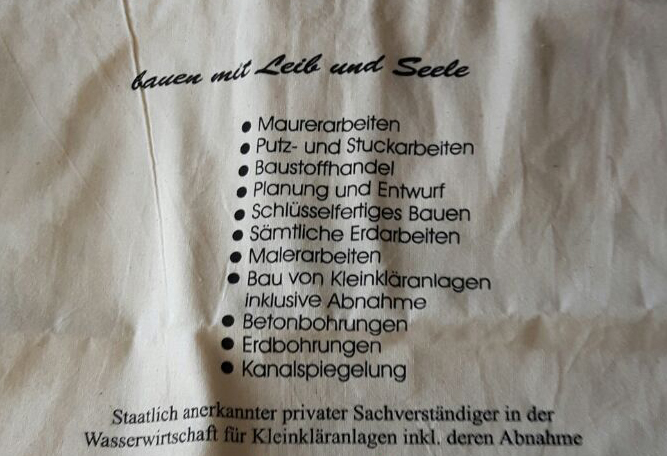
geometrische serifenlosen Linearantiqua gesucht
ich suche für einen Bekannten, die auf dem Bild zu sehenden Schriftarten.
Bei der Handwritten handelt es sich um die Brush script Std.. Hab ich grade noch rausgefunden. :-)
Könnt Ihr mir mit der Grotesk und der Serifenschrift helfen?
Leider handelt es sich um eine Stofftasche. Daher ist die Schrift auch nich besonders gut zu erkennen.
Die Aufzählung sollte eine Avant Garde Gothic sein, die Unterzeile irgendeine Times.
Vielleicht kannst du bei der Gelegenheit das Wort "bauen" korrigieren, das ist hier nämlich substantiviert und muss daher groß geschrieben werden. "Bauen mit Leib und Seele".